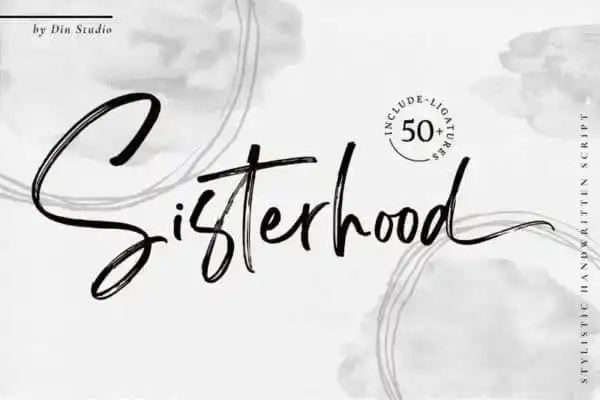
A Sisterhood Brush Font é uma elegante e sofisticada tipografia script criada a partir do uso de um pincel. Esta font foi desenvolvida por Din Studio, um designer chamado 99designs para quem busca adicionar um toque elegante em seus projetos visuais. Ideal para logos, cartazes, embalagens, livros, convites e até mesmo estampas personalizadas, a Sisterhood Brush Font se adequa perfeitamente a uma variedade de formatos gráficos como magazines, menus, cartões de visita e materiais promocionais. Ela é um recurso versátil para designers que desejam incorporar um ar sofisticado em seus trabalhos. Seja para estabelecimentos ou personalizações criativas, essa font será uma escolha atraente para aqueles buscando uma elegância moderna e única.